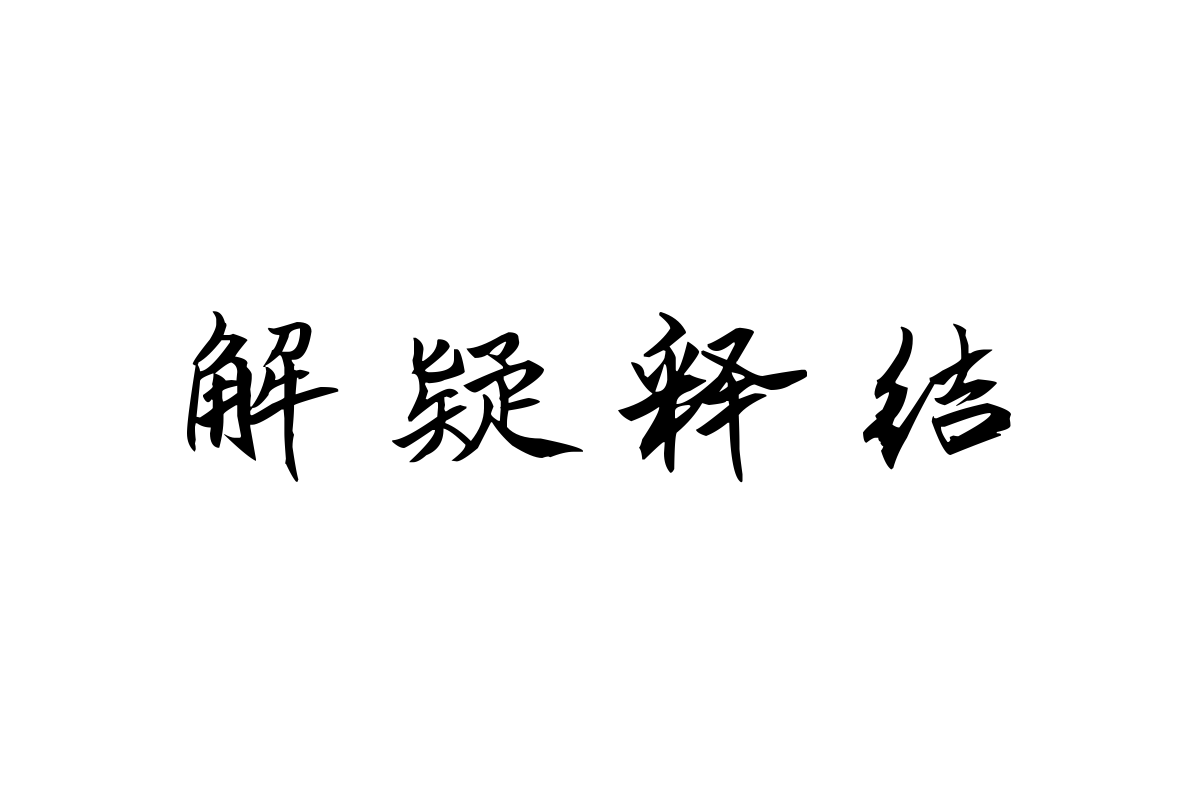
汉呈王天喜国潮风字体是一款具有独特设计和风格的中文字体。它结合了中国传统元素和现代设计,创造出一种独特的视觉体验。
这款字体的特点包括:
1. 字形结构:汉呈王天喜国潮风字体采用传统的汉字结构,但在某些部分进行了简化和优化,使其更加符合现代人的审美需求。这种结构使得字体在保持传统韵味的同时,也显得更加现代和时尚。
2. 笔画风格:这款字体的笔画风格独特,既有传统书法的韵味,又不失现代感。它的笔画线条流畅,富有弹性,给人一种轻松愉悦的感觉。
3. 字间距:汉呈王天喜国潮风字体的字间距设计得当,既不会过于拥挤,也不会过于稀疏。这种平衡的字间距使得整个字体看起来更加和谐,易于阅读。
4. 装饰元素:这款字体在设计中融入了一些中国传统的装饰元素,如云纹、波浪纹等。这些装饰元素不仅增加了字体的艺术感,还为整体设计增添了一份古典美。
5. 适用场景:汉呈王天喜国潮风字体适用于各种需要展现中国传统文化元素的场合,如广告、海报、网页设计、书籍封面等。它能够吸引人们的注意力,传达出一种独特的文化氛围。
总之,汉呈王天喜国潮风字体是一款独具特色的中文字体,它将传统与现代完美结合,为设计师们提供了丰富的创作灵感。